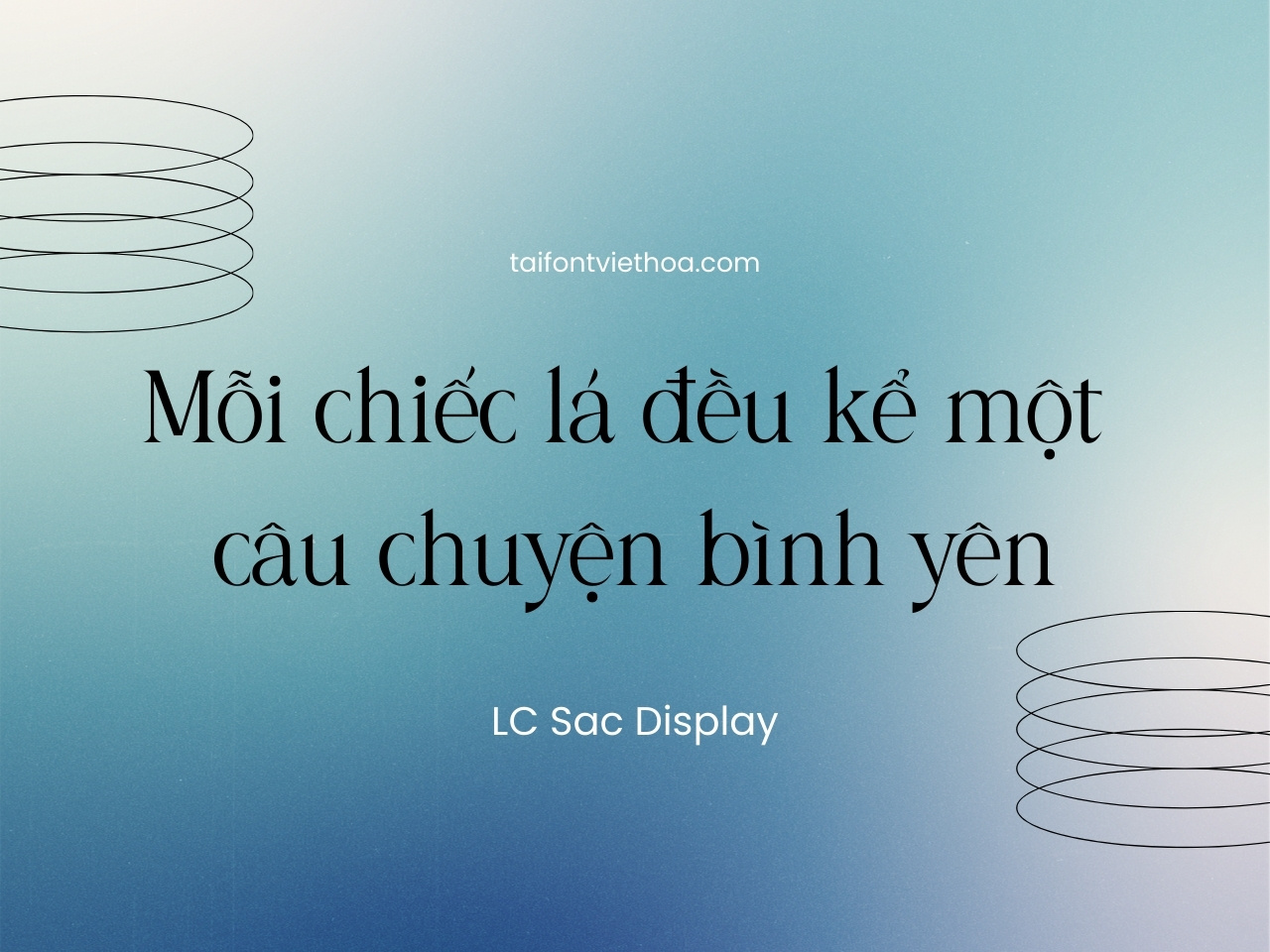
Font việt hóa Lc Sac Display Font Tiếng Việt
Tác giả Font: Nguyễn Quang Duy
Giới thiệu về font Lc Sac Display và phiên bản Việt hóa
Lc Sac Display là một kiểu chữ serif trang trí nổi bật, được thiết kế bởi Nguyễn Quang Duy – một nhà thiết kế font trẻ của Việt Nam. Font mang đậm hơi thở Á Đông đương đại, lấy cảm hứng từ phong cách đồ họa truyền thống và nét thủ công trong mỹ thuật xưa. Được xây dựng với bộ ký tự hoàn chỉnh, font không chỉ phục vụ cho trình bày tiếng Việt mà còn hỗ trợ hơn 70 ngôn ngữ khác dựa trên bảng mã Latin mở rộng.
Phiên bản Việt hóa được Nguyễn Quang Duy trực tiếp phát triển, tối ưu cho các ứng dụng hiển thị trong tiêu đề, thiết kế poster hoặc các sản phẩm ấn tượng mang tính cảm xúc. Các dấu tiếng Việt được xử lý thủ công, giữ nguyên bản sắc đồng thời đảm bảo tính tương thích kỹ thuật cao. Font này đã được taifontviethoa.com chọn lọc và giới thiệu tới cộng đồng thiết kế Việt như một lựa chọn độc bản, mang giá trị bản địa, phù hợp với các dự án văn hóa, sáng tạo và truyền thông thương hiệu độc đáo.
Vẻ đẹp serif cổ điển giao thoa cùng hiện đại
Lc Sac Display mang dáng vẻ serif trang trí nổi bật với cấu trúc chữ thanh mảnh nhưng đầy ngẫu hứng. Các chi tiết đuôi chữ, đầu móc và cấu trúc uốn lượn giúp font tạo điểm nhấn thị giác mạnh mẽ. Font được xây dựng với hệ chữ hoa đặc biệt, lý tưởng để dùng trong tiêu đề, bìa sách, thiệp mời hoặc thiết kế thương hiệu mang đậm tính nghệ thuật và cá nhân hóa.
Font này thích hợp cho nhiều lĩnh vực như giáo dục, công nghệ, văn hóa, quảng cáo, sản phẩm lễ hội hoặc thiệp chúc mừng. Những nhà thiết kế cần một kiểu chữ vừa trang nghiêm vừa bay bổng, dễ nhận diện sẽ thấy Lc Sac Display là công cụ lý tưởng để truyền tải thông điệp thương hiệu theo cách đầy sáng tạo và khác biệt.